Typo Fahrrad
Ein Traumfahrrad für jeden typophilen, das Type Bike von Juan Madrigal. Nach ein paar Touren wird das Weiß nicht mehr ganz so gut aussehen, aber dennoch ein Hingucker bleiben.
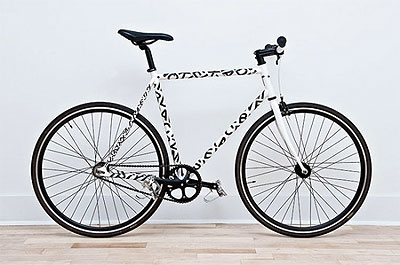
Das Fahrrad wurde mit der Helvetica Medium gestaltet, weitere Informationen gibt es auf Fubiz.